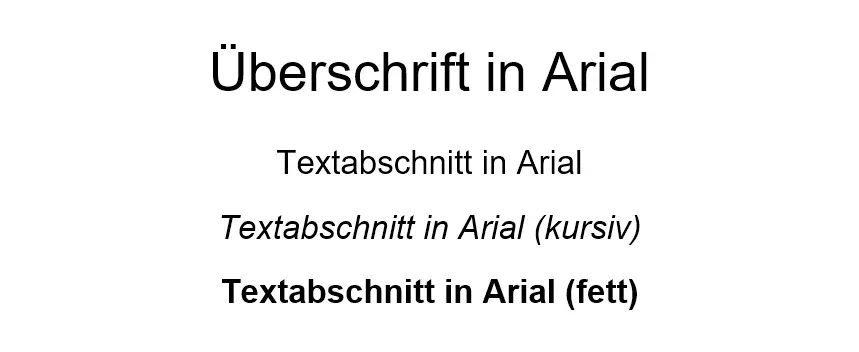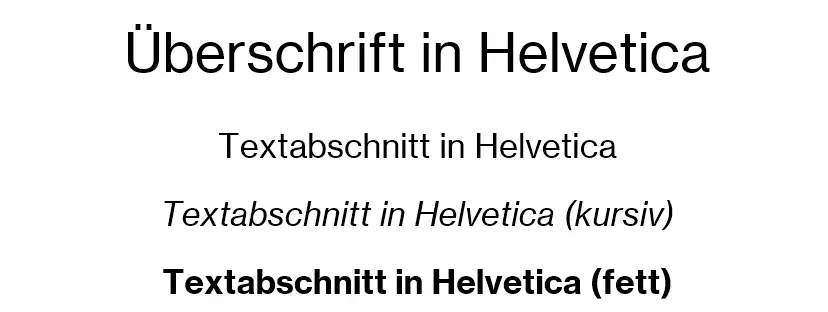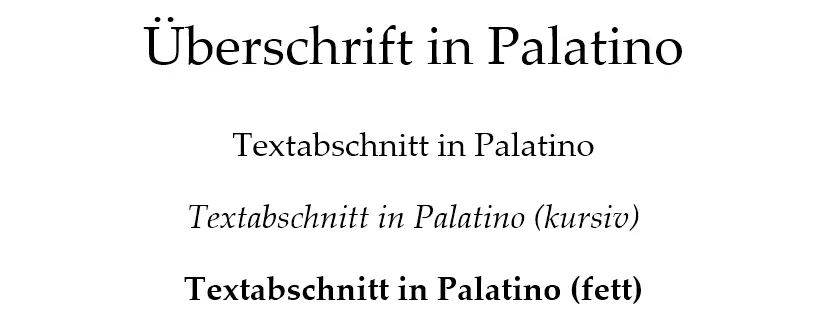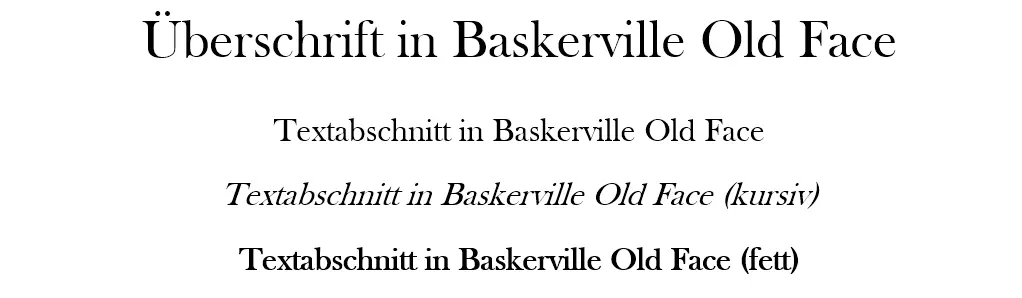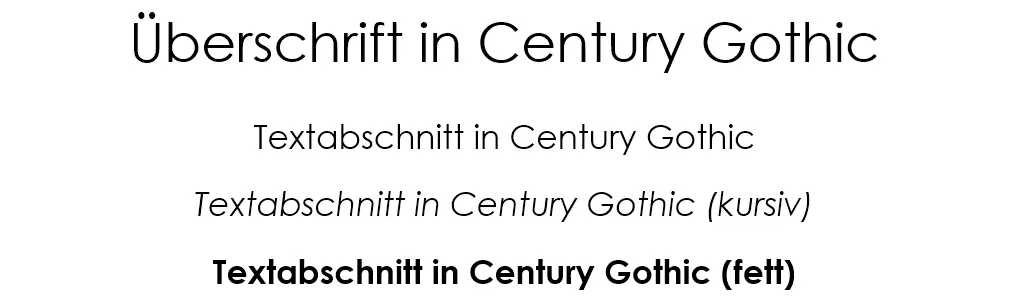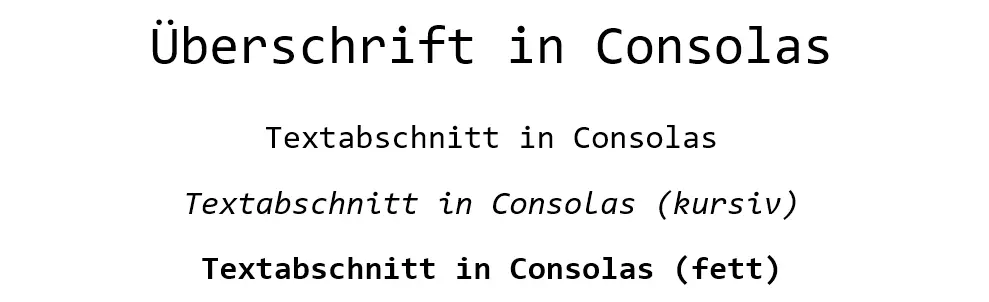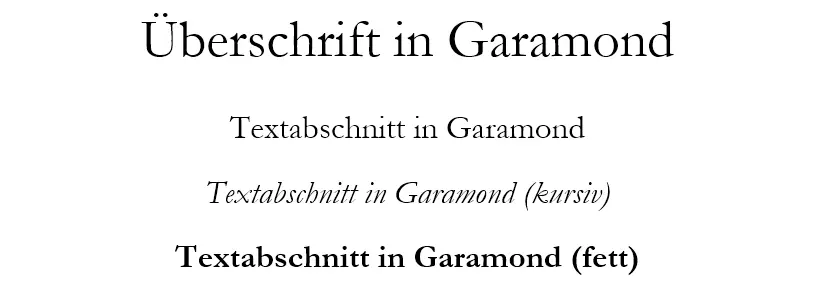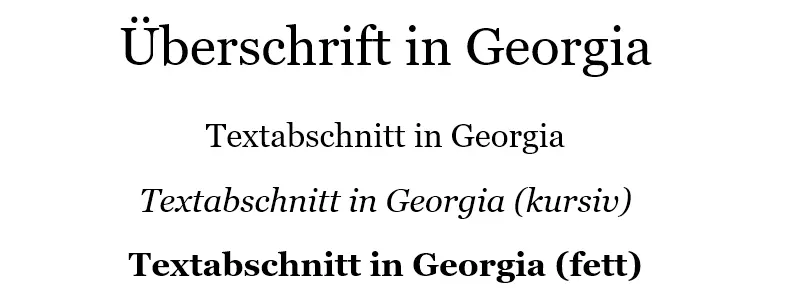
Webfonts: Mit Kreativität zu schöneren Websites
Als Webdesigner hatten Sie es nie so leicht wie heute, schicke Schriftarten für eine Website zu finden. Dank moderner Webfonts sind Ihrer Kreativität quasi keine Grenzen gesetzt. Mit der richtigen Kombination von Schriftarten, die den Charakter Ihrer Seite widerspiegeln und zu den sogenannten Web Safe Fonts zählen, hinterlassen Sie bei Ihren Lesern einen positiven Eindruck. Wir verraten Ihnen, was Webfonts sind und was websichere Fonts so wichtig macht.
Was sind Webfonts?
Als Webfonts bezeichnet man digitalisierte Schriftarten, die von gängigen Browsern schriftstilnah interpretiert werden können. Derartige Schriftarten sind primär für den Einsatz in HMTL- bzw. XHTML-Dokumenten – also für den Einsatz im Web – vorgesehen. Webfonts zeichnen sich dadurch aus, dass sie unabhängig von dem verwendeten Betriebssystem funktionieren, da sie beim Aufruf einer Website nicht aus den lokalen Schriftensammlungen, sondern von einem externen Webserver geladen werden. Zu diesem Zweck müssen die gewünschten Webfonts lediglich mithilfe der CSS-Regel @font-face eingebunden und im Font Stack (dt. „Schriftstapel“) angegeben werden.
Warum sind websichere Schriften so wichtig?
Seit der Einführung von @font-face in CSS2 lassen sich aus technischer Sicht alle Schriftarten in Webprojekte einbinden. Zuvor hatten Webdesigner lediglich eine kleine Auswahl an Standardschriften wie Arial oder Times New Roman zur Verfügung. In diesem Zusammenhang wurde auch der Begriff der Web Safe Fonts (dt. websichere Fonts) geprägt, der zunächst diese für eine reibungslose Webdarstellung unverzichtbaren Standard-Fonts kennzeichnete.
Durch die heutige riesige Auswahl an websicheren Schriften haben es Webdesigner mittlerweile deutlich einfacher, Corporate-Design-Vorgaben zu erfüllen. Web Safe Fonts sind daher eine der wichtigsten Grundlagen, um übergreifende Marketingstrategien umzusetzen, was sie für einen durchschlagenden Erfolg im Web für viele Unternehmen nahezu unverzichtbar macht.
Webfont-Kategorien und ihre Anwendung
Mit dem Begriff Schriftart fasst man sämtliche Schriftzeichen zusammen, die nach einem identischen Gestaltungskonzept entworfen wurden. Existieren mehrere Varianten solch einer Schriftart, die sich z. B. hinsichtlich der Strichstärke oder Laufweite unterscheiden, dann bezeichnet man sie als Schriftfamilie. So gehören beispielsweise die Schriften Segoe UI, Segoe Light und Segoe Semibold zu einer Schriftfamilie.
Die unterschiedlichen websicheren Schriften eignen sich für verschiedene Einsatzgebiete. Bei der Auswahl einer Schriftart sollte man vor allem auf zwei Dinge achten: die Lesbarkeit der Schrift und ihre emotionale Wirkung. Dabei spielt auch das Medium eine große Rolle. Bei sogenannten Serifenschriften weisen die einzelnen Buchstaben am Ende der Buchstabenbalken kleine Querstriche auf, die ein flüssiges Lesen kleingedruckter Texte erleichtern. Für das Lesen am Monitor ist diese Schriftart allerdings nicht immer ideal.
Funktion und Position im Text sollten die Wahl der Webfonts ebenfalls beeinflussen: Während besonders auffällige Schriften in den Überschriften für die gewünschte Aufmerksamkeit sorgen, wirken sie im Fließtext oft deplatziert. Aus diesem Grund verwenden Webdesigner häufig mehrere unterschiedliche Schriftarten oder Schriftschnitte (so nennt man die Varianten innerhalb einer Schriftfamilie) in einem Text. Allerdings sollte man es hierbei nicht übertreiben, da die Website sonst schnell überladen wirkt.